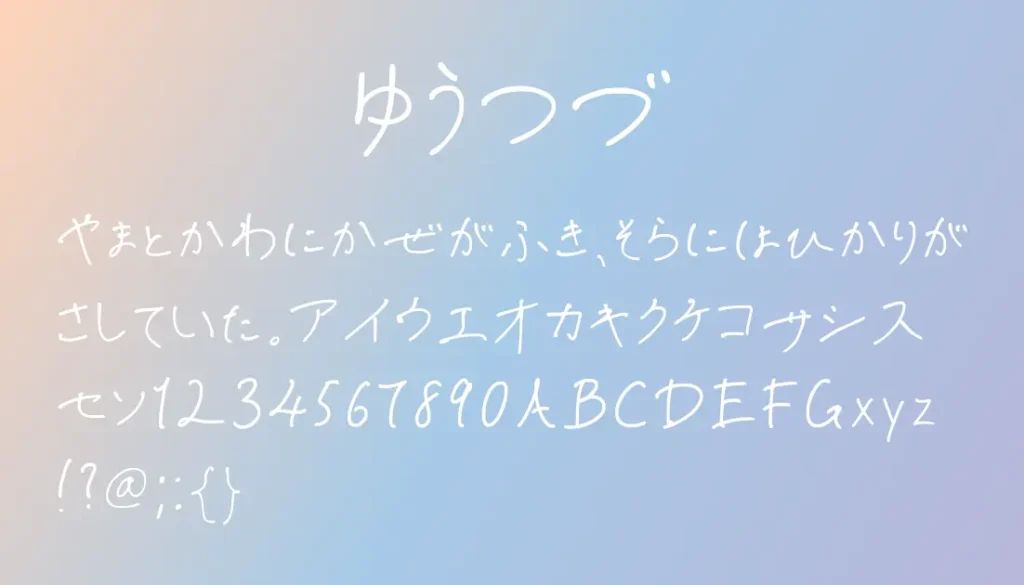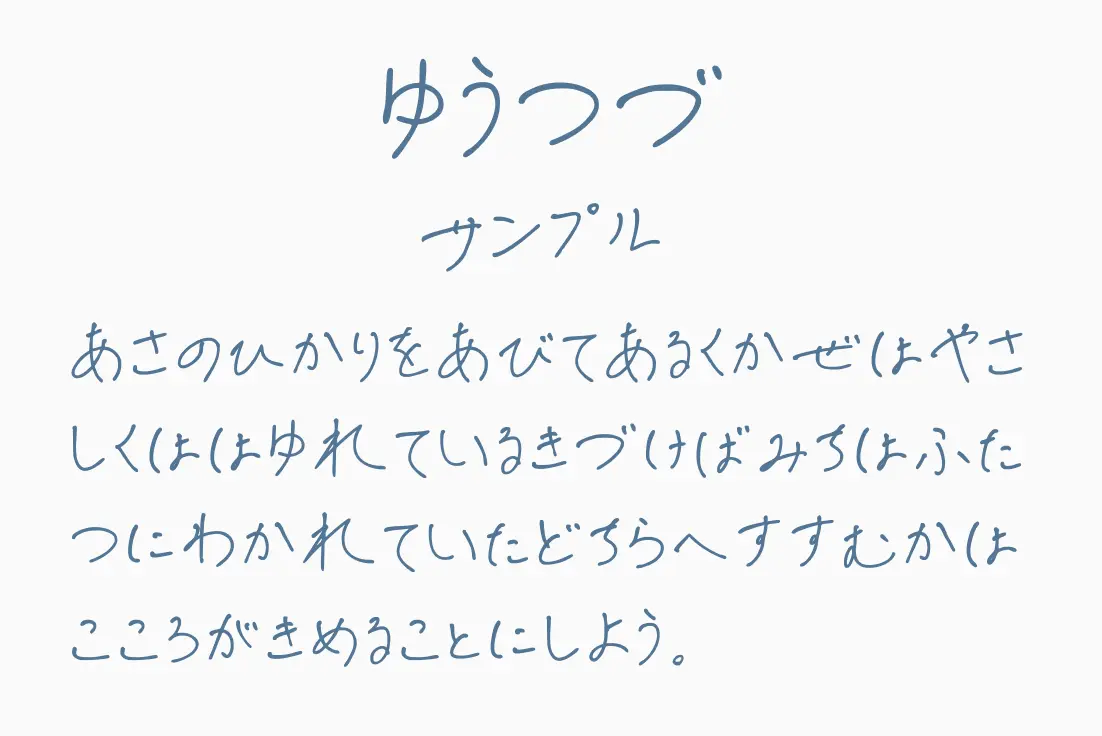
やわらかな手書きの流れをそのまま文字にしたようなナチュラルな雰囲気の日本語フォントです。線の太さにゆらぎがあり、書き文字らしい温度感が出るのが特徴。ラフな筆記感を残しながらも読みやすさが保たれているため、タイトルやメッセージ、SNS画像などに自然に溶け込みます。力の抜けた柔らかな印象で、手紙・日記・雰囲気系デザインなどにぴったりな書き文字系フォントです。
夕月(Yutsudu)ゆうつづ